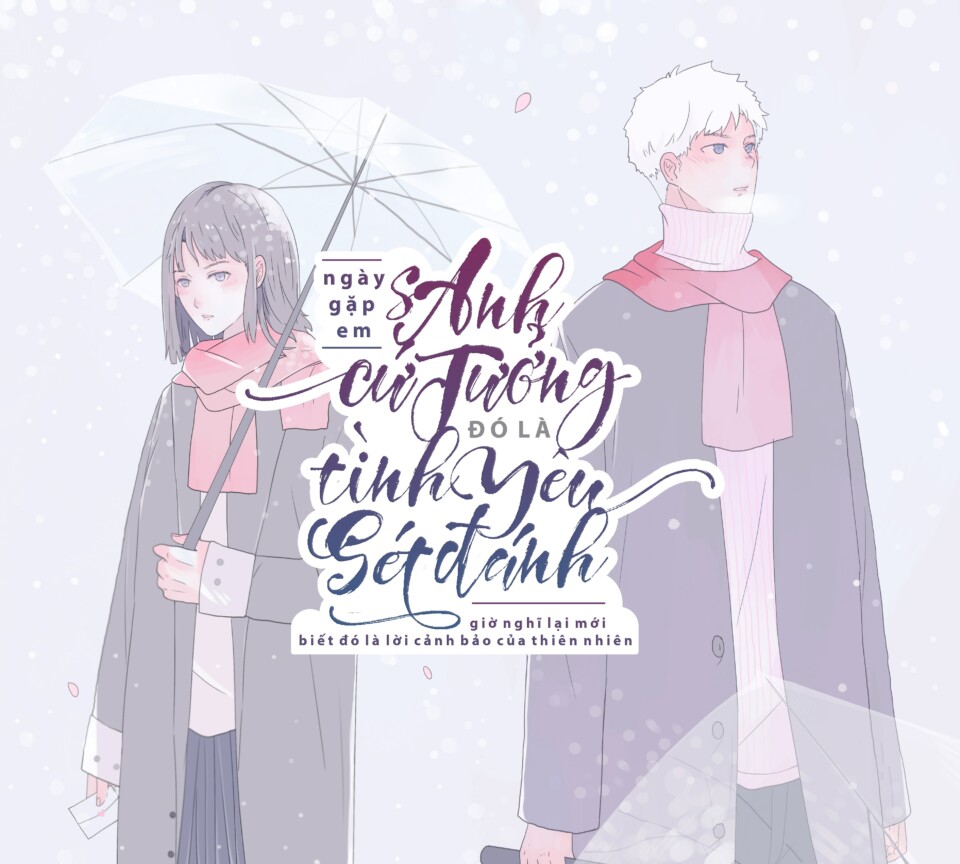
Tải ngay Font Việt hóa MTD Girly Things: Sự lựa chọn hoàn hảo cho thiết kế nữ tính và dự án học đường
Trong thế giới thiết kế đồ họa và tài liệu học tập, việc lựa chọn một bộ Font Chữ phù hợp có thể tạo nên sự khác biệt lớn. Đặc biệt, đối với các dự án cần sự mềm mại, dễ thương và cá tính, việc tìm kiếm các phông chữ đẹp Việt hóa là vô cùng quan trọng. Hôm nay, chúng ta sẽ cùng khám phá một cái tên đang rất được yêu thích: Font Việt hóa MTD Girly Things. Đây không chỉ là một font chữ có tên gọi dễ thương mà còn là giải pháp tuyệt vời cho những ai đang tìm kiếm sự hoàn hảo từ nét chữ đến khả năng tương thích tiếng Việt.
Tại sao Font Việt hóa MTD Girly Things lại được ưa chuộng trong giới học sinh, sinh viên?
Sự phổ biến của Font Việt hóa MTD Girly Things không phải là ngẫu nhiên. Font chữ này được thiết kế với những đường nét uốn lượn, bay bổng, mang đậm chất “girly” (nữ tính) nhưng vẫn giữ được độ rõ ràng cần thiết. Đối với học sinh, sinh viên, đặc biệt là các bạn nữ, việc sử dụng font này trong các bài thuyết trình, báo cáo nhóm, hay thậm chí là thiết kế bìa sổ tay, thiệp mời cho các sự kiện của trường (như lễ tốt nghiệp, sự kiện cuối năm học) giúp tăng tính thẩm mỹ và cá nhân hóa sản phẩm của mình.
Ứng dụng đa dạng trong các dự án học tập
Một trong những lợi ích lớn nhất của việc sử dụng các font chữ việt hóa là khả năng hiển thị đầy đủ và chính xác các dấu tiếng Việt, từ đó giúp người dùng tránh được lỗi font phiền toái. Font này rất phù hợp cho:
- Thiết kế poster, infographic: Tạo điểm nhấn mềm mại cho các bài trình bày.
- Sổ tay học tập và Planner: Biến việc ghi chép trở nên thú vị hơn.
- Thiệp chúc mừng và thiệp mời: Đặc biệt là trong các dịp kỷ niệm của trường hoặc chuẩn bị cho kỳ thi tốt nghiệp THPT.
Đặc điểm nổi bật của bộ phông chữ MTD Girly Things
MTD Girly Things, sau khi được Việt hóa, đã trở thành một tài sản quý giá cho cộng đồng thiết kế Việt. Bộ font này nổi bật nhờ sự kết hợp hài hòa giữa phong cách viết tay (handwritten style) và sự tinh tế, dễ đọc. Nó không quá kiểu cách như một số font trang trí khác, nhưng đủ để tạo ra cảm giác ấm áp và thân thiện.
Cấu tạo và tính năng kỹ thuật:
- Đầy đủ ký tự tiếng Việt: Đây là yếu tố then chốt, bao gồm tất cả các dấu sắc, huyền, hỏi, ngã, nặng, và các chữ cái đặc biệt như ă, â, ê, ô, ơ, ư. Việc này đảm bảo rằng các tài liệu học thuật hoặc sáng tạo của bạn luôn chuyên nghiệp và không bị lỗi font.
- Phong cách “hand-drawn”: Mang lại cảm giác thủ công, rất phù hợp với xu hướng thiết kế cá nhân hóa hiện nay, nhất là trong các dự án về giáo dục và sáng tạo.
So sánh với các font chữ thư pháp khác
Trong khi các font thư pháp truyền thống thường mang tính trang trọng và cổ điển, thì MTD Girly Things lại thiên về sự trẻ trung và hiện đại. Nó là cầu nối giữa sự nghiêm túc của font chữ học thuật và sự bay bổng của font chữ nghệ thuật. Điều này làm cho nó trở thành LSI keyword quan trọng khi người dùng tìm kiếm “font chữ đẹp cho dự án học đường” hoặc “cách thiết kế tài liệu thu hút”.
Tóm lại, Font Việt hóa MTD Girly Things là một tài nguyên thiết kế không thể thiếu cho những ai yêu thích sự nữ tính, đáng yêu và muốn tạo ra những sản phẩm học thuật, sáng tạo có tính thẩm mỹ cao. Từ việc thiết kế bìa luận văn, trang trí bài thuyết trình, cho đến việc cá nhân hóa các công cụ học tập, font chữ này đều mang lại trải nghiệm tuyệt vời. Việc lựa chọn một bộ Font Chữ chất lượng, được Việt hóa hoàn chỉnh, chính là bước đầu tiên để nâng cao chất lượng công việc và học tập của bạn. Hãy tải và trải nghiệm ngay hôm nay để thấy sự khác biệt mà MTD Girly Things mang lại!